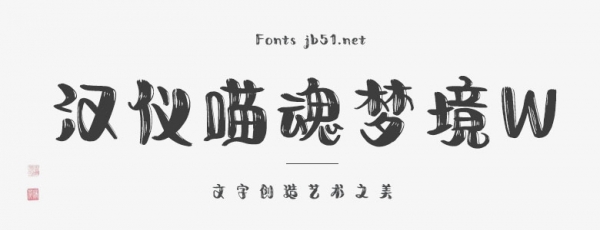
漢儀喵魂夢(mèng)境W是一款賞心悅目、百看不厭的書法藝術(shù)字體,字體線條粗細(xì)適中,筆畫隨性,結(jié)構(gòu)肆意灑脫,具有很好的視覺感,適合于文化類的宣傳設(shè)計(jì)、商業(yè)類品牌的廣告和產(chǎn)品包裝設(shè)計(jì)以及個(gè)性化文字排版等較多場景。